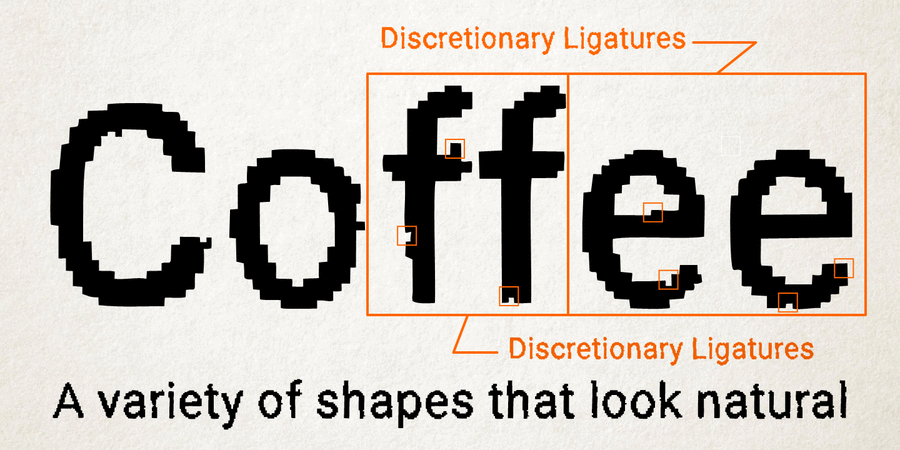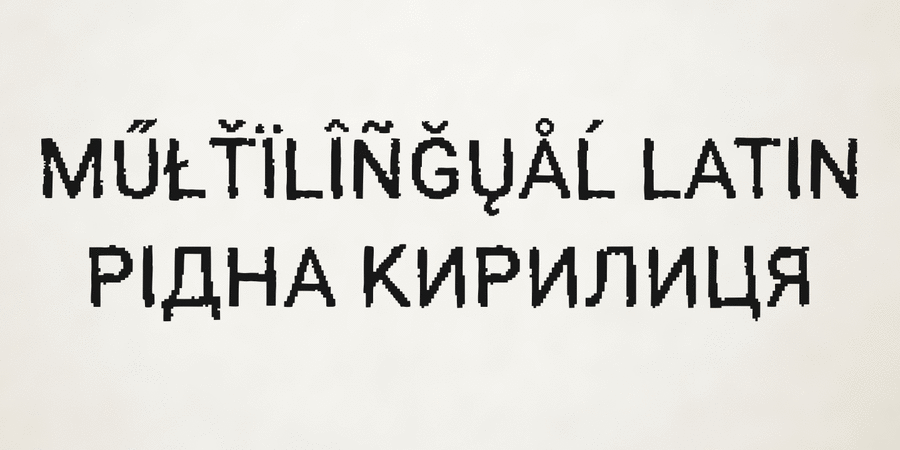
Шрифтова пара з Thalweg Bold (1 з 2)Опис шрифта Lo Fi CopyLo-Fi Copy – хороший спосіб додати вашому дизайну вінтажного аналогового вигляду. Грубі пікселі мають хаотичні похибки, як при пошкодженому сигналі факс-модема або на роздруківці з низькою роздільною здатністю. Шрифт розробив Лук'ян Турецький у 2020 році.
Особливості сімейства шрифтів Lo Fi CopyХіт десятиліття:
Хіт 1980-х Хіт 1990-х Lo Fi Copy підтримує 83 мовиУкраїнська, Англійська, Німецька, Польська, Португальська, Іспанська, Французька, Російська, Чеська, Голландська, Італійська, Шведська, Турецька, Фінська, Білоруська, Сербська, Болгарська, Естонська, Литовська, Албанська, Африкаанс, Баскська, Бретонська, Валенсаска, Galician, Гельська (Шотландська), Данська, Індонезійська, Ірландська, Ісландська (Win), Каракалпацька, Каталонська, Норвезька, Окситанська, Ретороманська, Самі Лулі, Тсванська, Узбецька (Лат.), Фарерська, фризька, Чаморро, Естонська (Win), Південносаамська, Албанська (Win), Угорська, Верхньолужицька, Карельська, Латвійська (Mac), Литовська (Mac), Маорійські (Mac), Молдавська (Лат.), Нижньолужицька, Румунська (Win), Словацька, Словенська, Туркменська (Лат.), Хорватська (Win), Естонська (Mac), Курдська, Латишська, Маорійські, Руминська, Абазинська, Аварська, Агульська, Адигейська, Даргинську, Інгуську, Кабардино-Черкеська, Кабардинська, Карачаєво-Балкарська, Кумицька, Лакська, Лезгинська, Македонську, Мордовсько-Мокшанська, Мордовсько-Ерзянська, Ногайська, Рутульська, Табасаранська, Татська, Цахурська, Чеченська Функції сімейства шрифтів Lo Fi CopyЗастосування гарнітури у верстці:
Асоціації з сімейством шрифтів Lo Fi CopyОсобистість і характер гарнітури:
нейтральний, середній, звичайний, діловий, універсальний, зрозумілий, врівноважений, космополітичний, ненав'язливий, стандартний, помірний, глобалізований, глобалістічний, прагматичний, практичний, невиразний, міський, байдужий, офісний, офіційний, іронічний, побутовий, грубий, нервовий